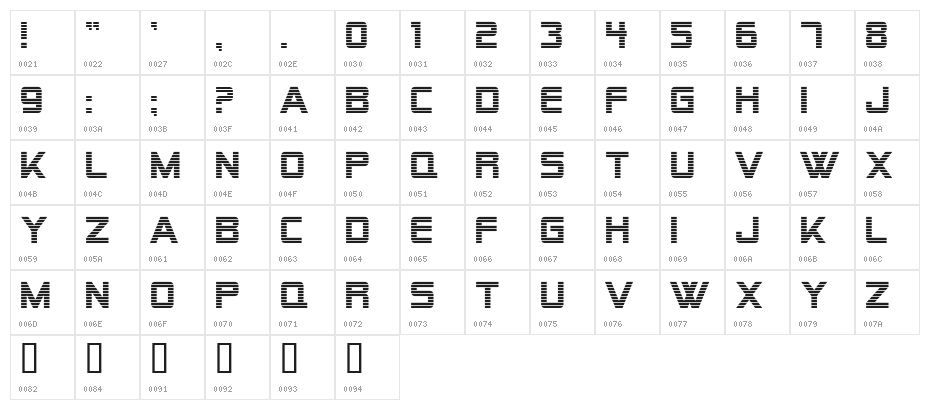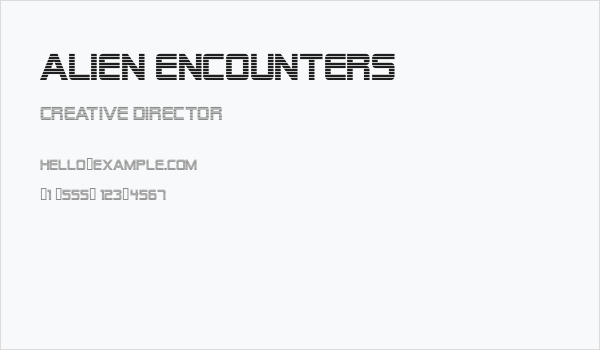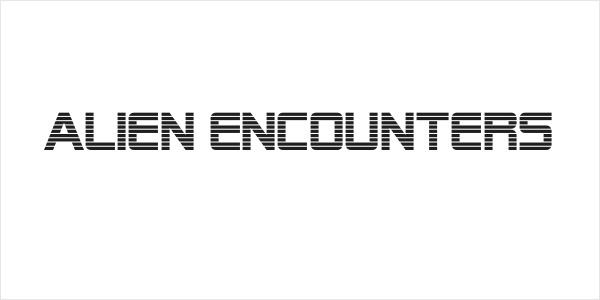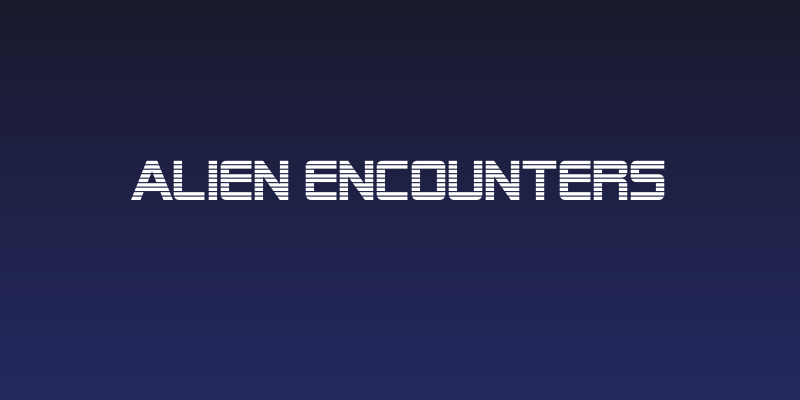
Alien Encounters Font
✎ Futuristic
| श्रेणियाँ | Futuristic |
| समग्र शैली | Futuristic |
| उपयोग का मामला | Headlines, Logos |
| सुझाए गए प्रोजेक्ट | Ideal for sci-fi movie posters, tech company logos, video game interfaces, and digital art projects. |